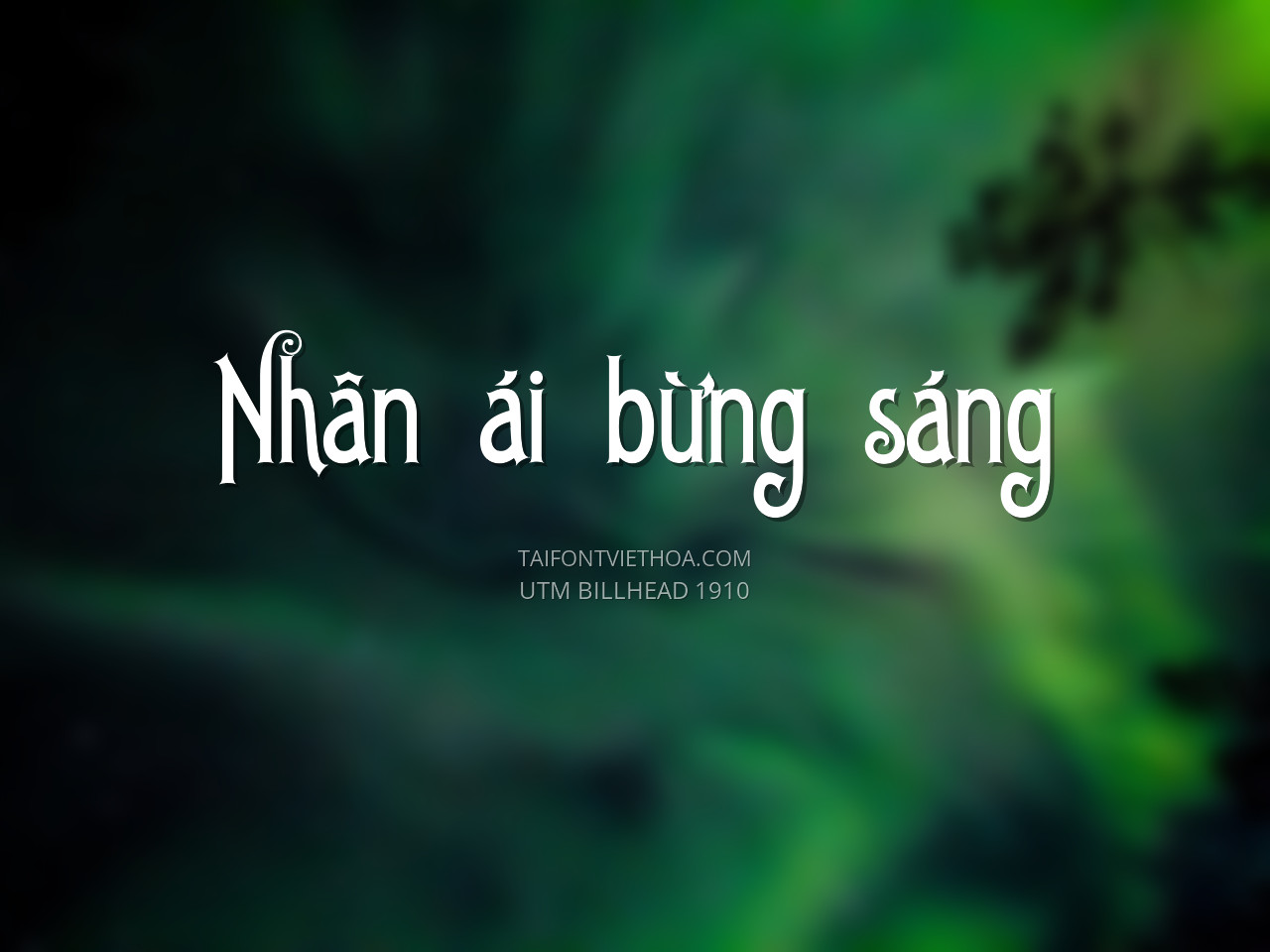
Giới thiệu về font UTM Billhead 1910
UTM Billhead 1910 là phiên bản Việt hóa của font Billhead 1910 – một kiểu chữ vintage đặc trưng với phong cách thiết kế hoài cổ, lấy cảm hứng từ các hóa đơn và tài liệu thương mại đầu thế kỷ 20. Font gốc nổi bật với các nét chữ serif có chân, đường nét chi tiết và tinh tế, mang lại vẻ đẹp cổ điển và sang trọng. Phiên bản Việt hóa đã được hoàn thiện để hỗ trợ đầy đủ tiếng Việt cùng hơn 200 ngôn ngữ khác, mở rộng khả năng sử dụng trong các dự án thiết kế mang phong cách retro và lịch sử.
Đặc điểm thiết kế và ứng dụng của UTM Billhead 1910
UTM Billhead 1910 sở hữu cấu trúc serif với các nét chữ mảnh mai, chân chữ tinh tế và độ tương phản nhẹ nhàng. Font có thiết kế cân đối, dễ đọc và rất phù hợp để tạo điểm nhấn trong các thiết kế vintage, retro hoặc hoài cổ. Font còn được trang bị nhiều ligature và glyph thay thế để tăng tính linh hoạt trong thiết kế.
Font thích hợp sử dụng trong các thiết kế bao bì sản phẩm, poster, thiệp mời, danh thiếp và các ấn phẩm truyền thông mang phong cách vintage và cổ điển. Các ngành nghề phù hợp gồm: nghệ thuật, xuất bản, thời trang, tổ chức sự kiện và thiết kế nội thất.